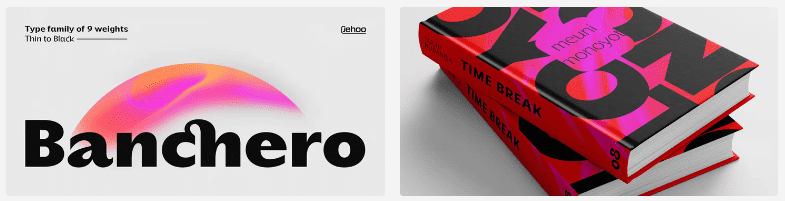
Название: Banchero Font Family (2022)
Banchero вдохновлен очаровательным винтажным дизайном, привнося непринужденность и элегантность в современную типографику. Сильная основа sans имеет изящные произвольные лигатуры между чувствительными буквами, поэтому этот шрифт подходит для всех видов дизайна - от заголовков до текста, от плакатов до редакционных статей - Banchero будет выделяться.
Его мощь и универсальность также обусловлена наличием 9 полных весов, каждый из которых содержит более 520 глифов. Эти веса тщательно проработаны и обрезаны для достижения наилучшего результата в вашем следующем дизайне.
Название: Banchero Font Family (2022)
Banchero вдохновлен очаровательным винтажным дизайном, привнося непринужденность и элегантность в современную типографику. Сильная основа sans имеет изящные произвольные лигатуры между чувствительными буквами, поэтому этот шрифт подходит для всех видов дизайна - от заголовков до текста, от плакатов до редакционных статей - Banchero будет выделяться.
Его мощь и универсальность также обусловлена наличием 9 полных весов, каждый из которых содержит более 520 глифов. Эти веса тщательно проработаны и обрезаны для достижения наилучшего результата в вашем следующем дизайне.